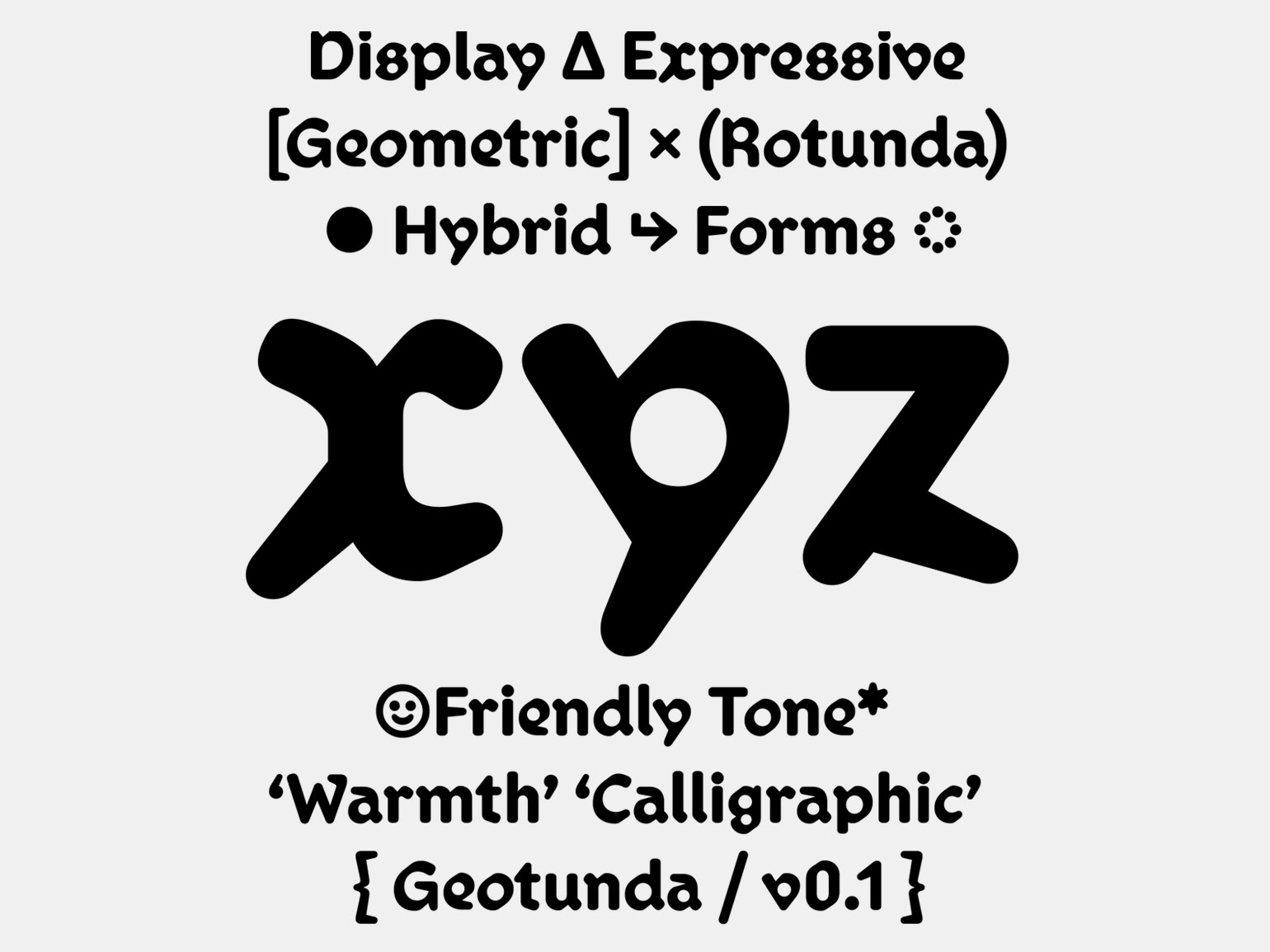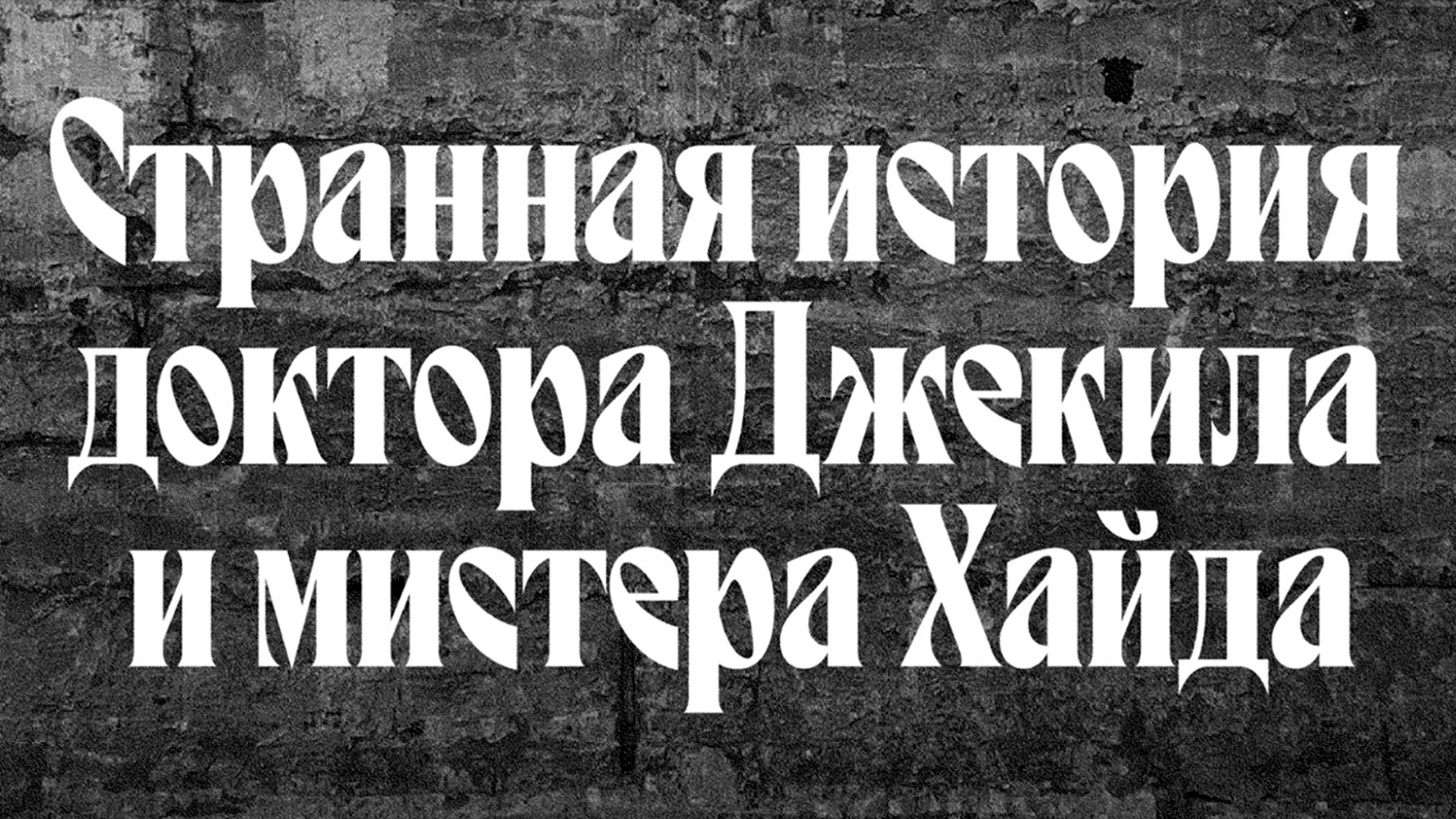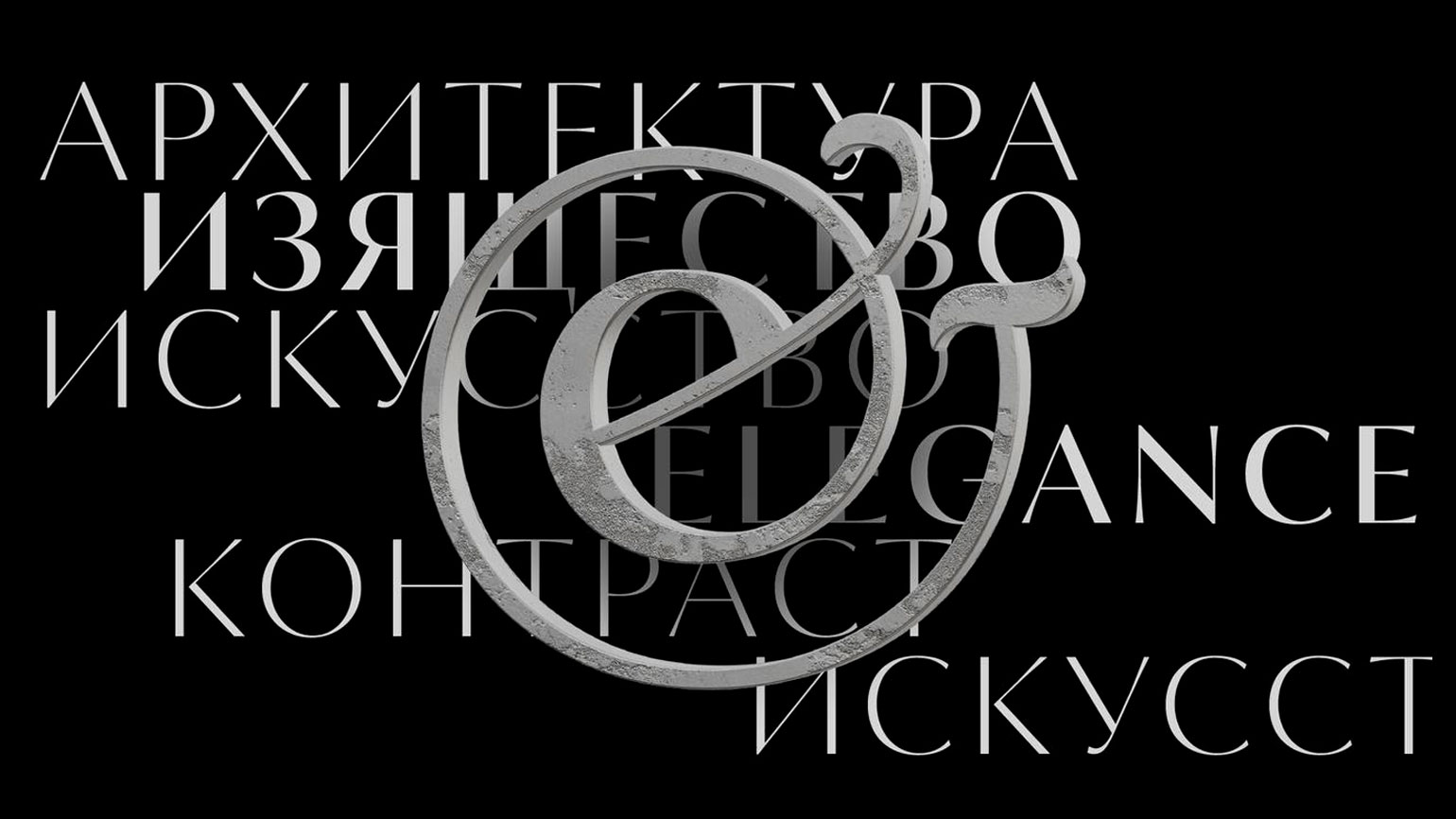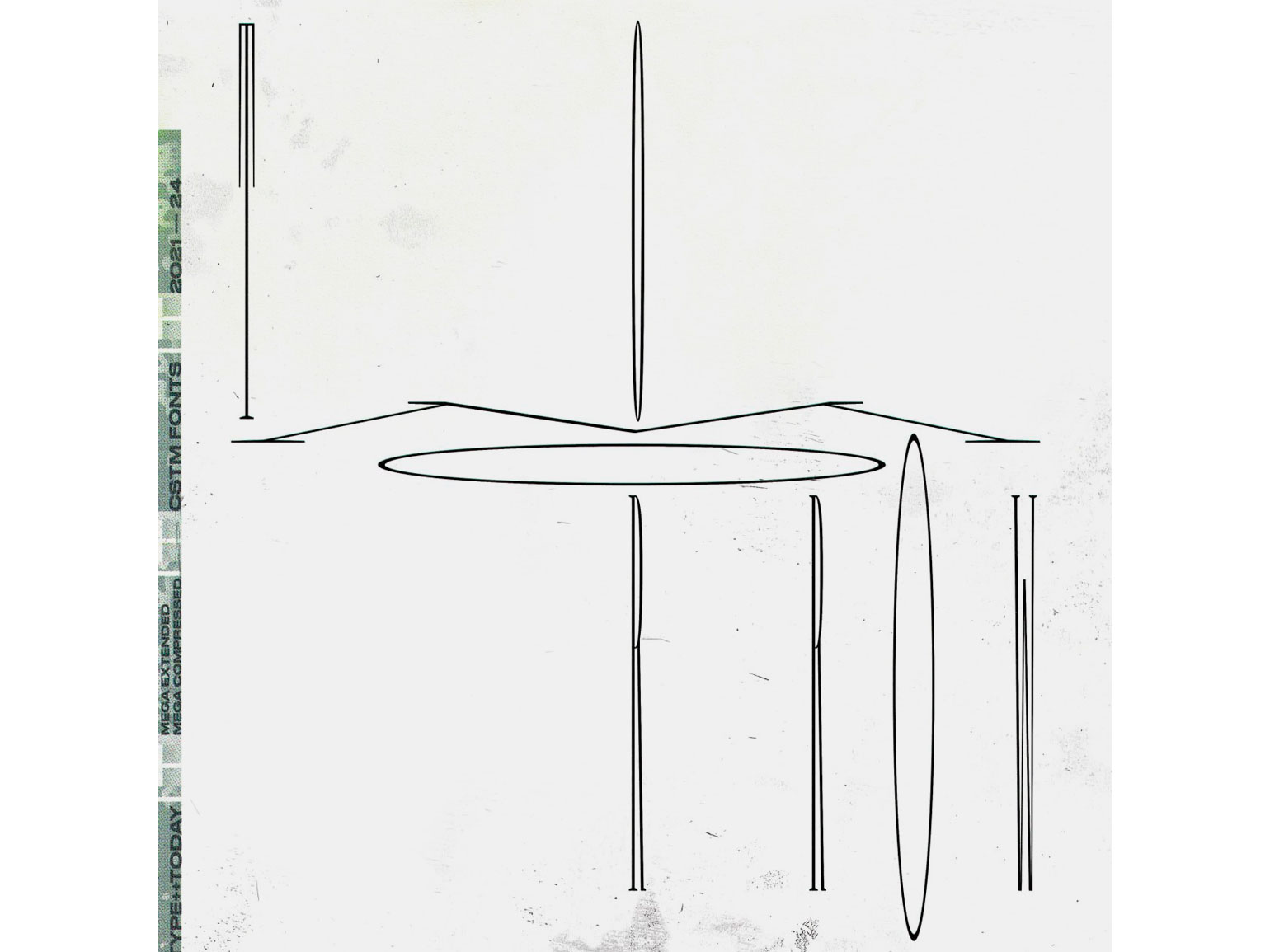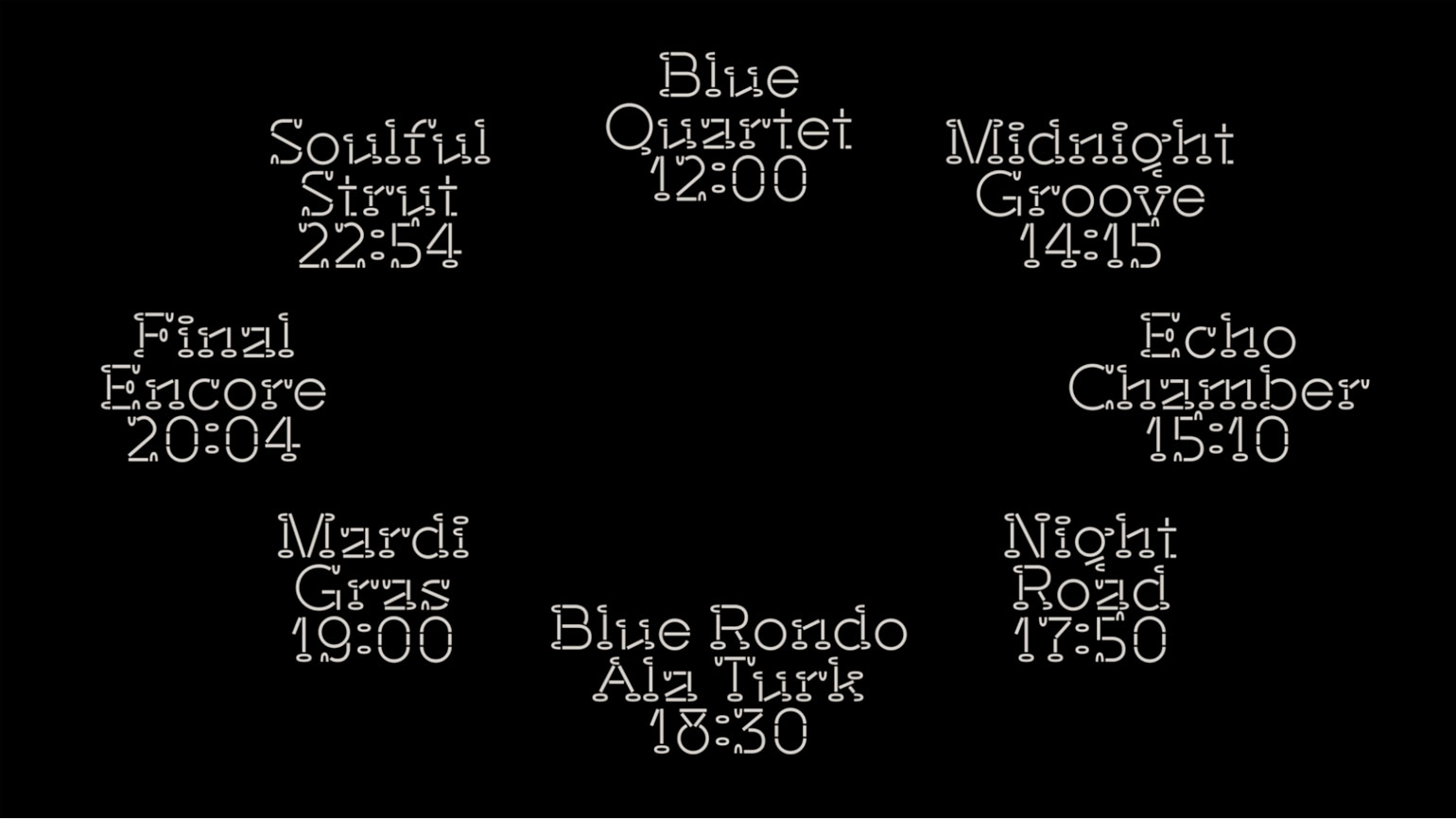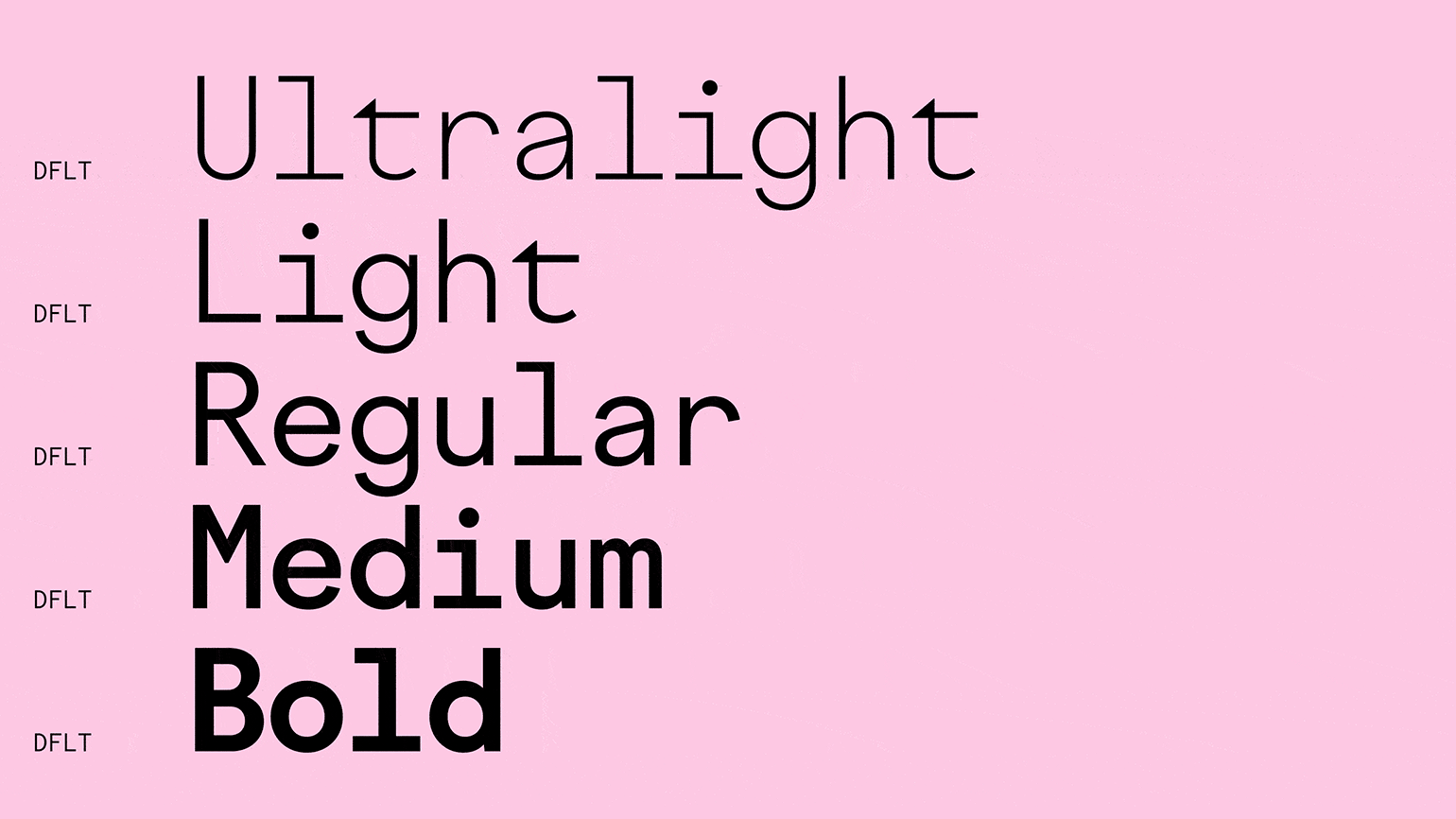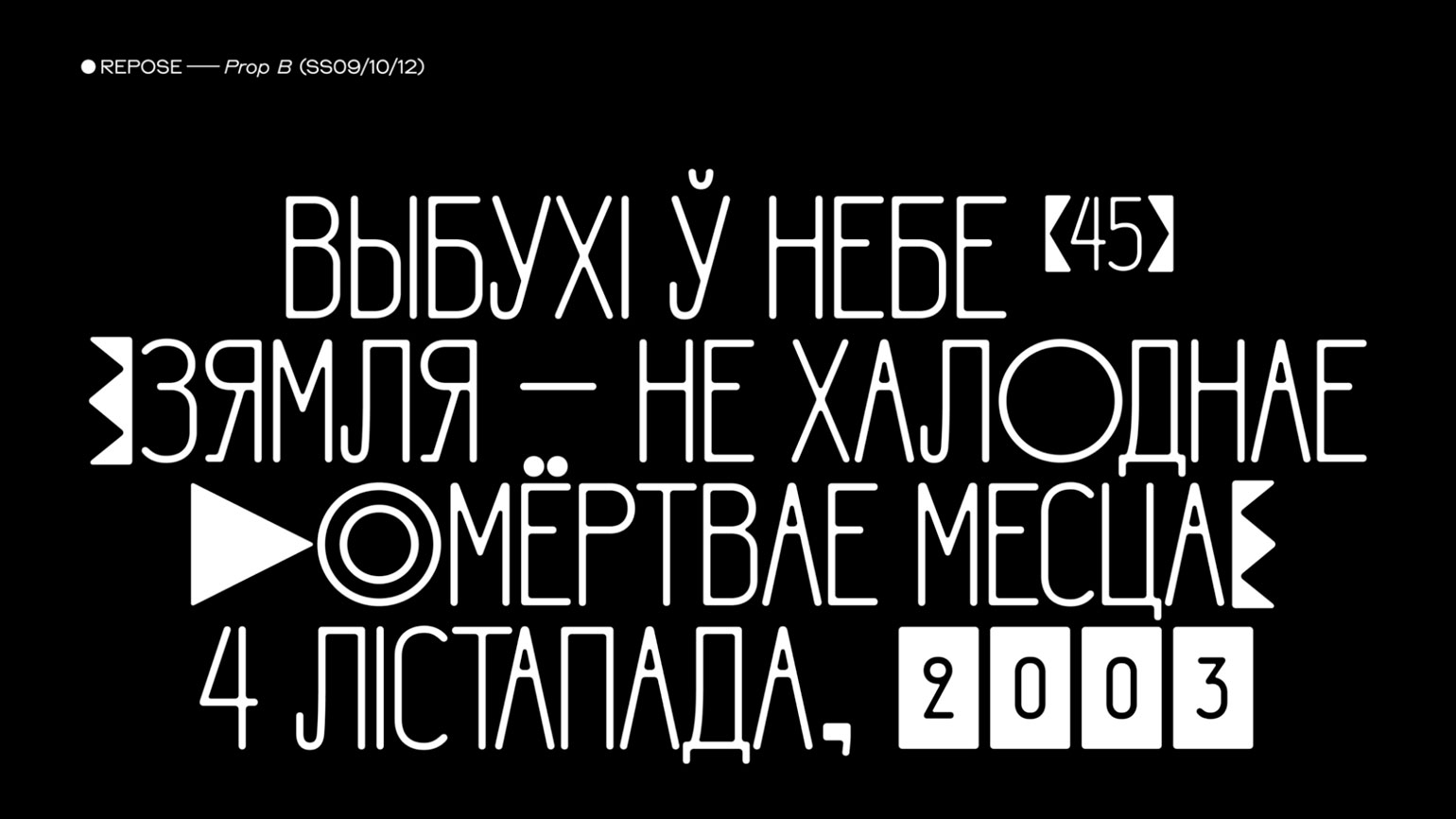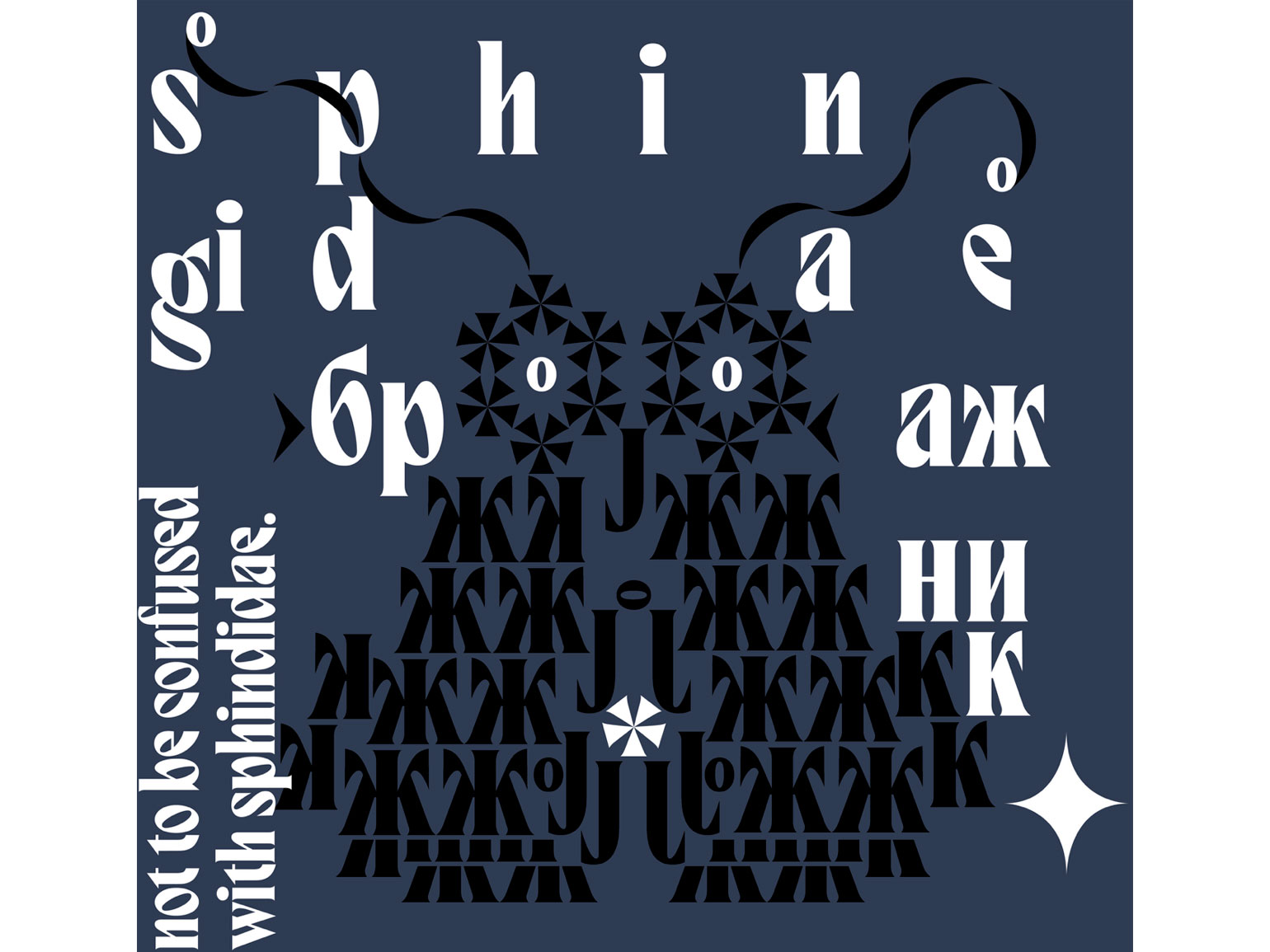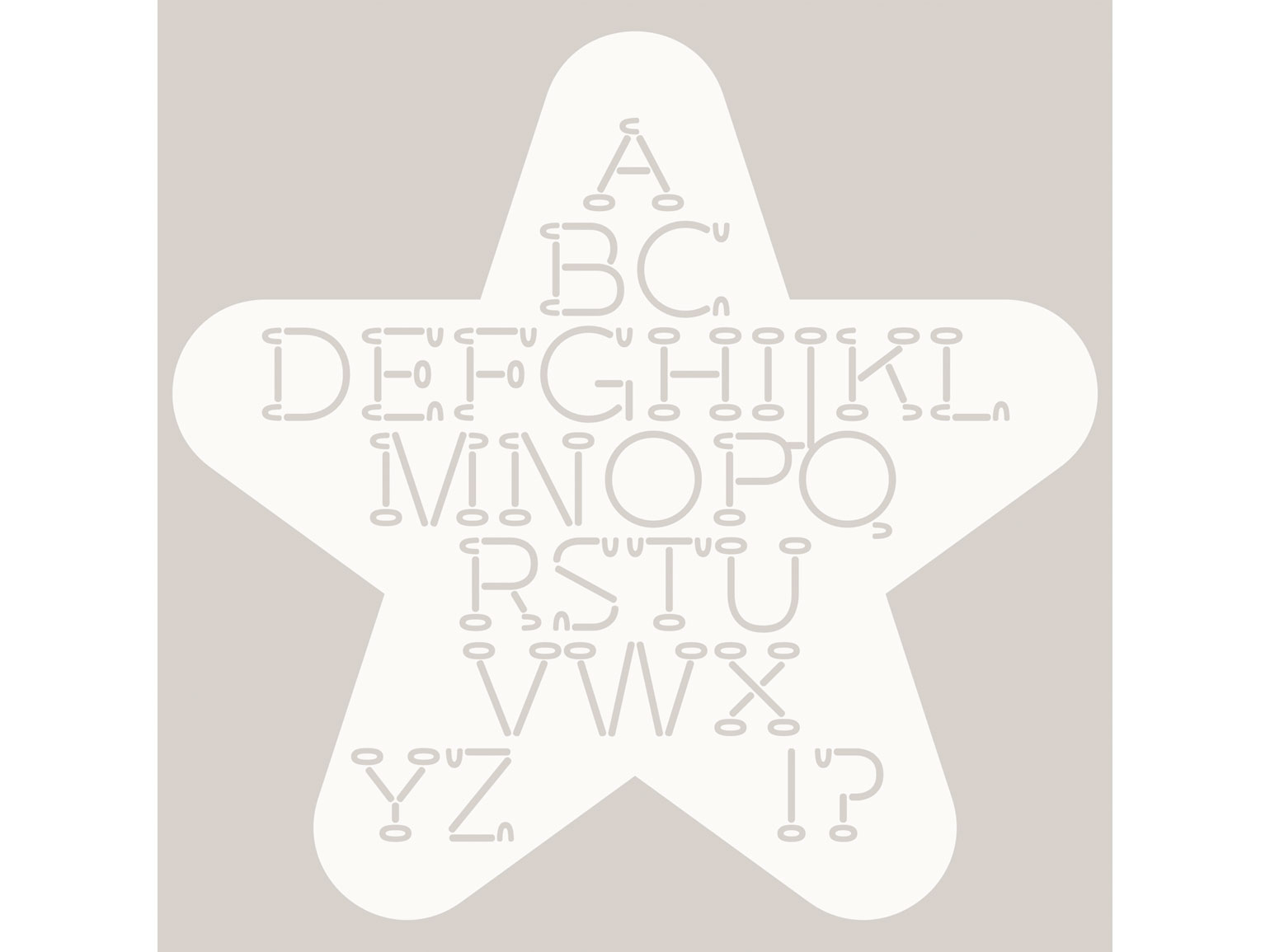
Новые шрифты: элегантная антиква CoFo Raffine, «дружелюбная» Geotunda и перерождение Pragmatica
Эксперты делятся любимыми новинками для экспериментов в дизайн-проектах.
Спросили у шрифтовых дизайнеров и арт-директоров, что сейчас вдохновляет их в типографике: какие новые шрифты заслуживают внимания, где их найти и как использовать для реальных задач.
Repose
Сегодня Филипп Ноймайер — главный человек в кириллице из тех, для кого эта письменность не является родной. Его эксперименты — кладезь интересных и неординарных решений. Я хочу отметить один из таких — свежий релиз Repose. Это тонкий, но от этого не менее брутальный гротеск для ярких и больших надписей. Полностью прописная касса ≠ скучный набор, семейство состоит из двух версий, в которых отличаются графемы, а каждая версия — из трёх вариантов скруглений. Самое время для безумных комбинаций!
Изображение: Филипп Ноймайер / type.today
Guidy
Дипломный проект Матвея Малкина — универсальный открытый геометрический гротеск для навигации. Шрифт уверенно чувствует себя на любой табличке, указателе или схеме. У знаков хорошие просветы и широкие апроши, что делает его прекрасно читаемым с большого расстояния и хорошо различимым в движении.
Guidy поддерживает более ста языков, включая большое количество знаков расширенной кириллицы, а также имеет в комплекте сет иконок с возможностью набора с помощью функций OpenType. А ещё он бесплатный!
Изображение: Матвей Малкин / НИУ ВШЭ
CoFo Raffine
Эта восхитительная, невероятно элегантная антиква авторства Ольги Коваленко — один из самых ярких релизов последних дней. Вдохновлённая титрами из немецкого немого вестерна начала ХХ века, эта гарнитура не оставит равнодушным ни одного любителя букв!
CoFo Raffine разносторонняя, в меру непредсказуемая и небанальная. Из особенностей — утончённый контраст штрихов, разноширинные пропорции, бросающие вызов устоявшимся шрифтовым традициям, а также большое количество лигатур, альтернатив и вариантов с росчерками для яркого, нескучного набора.
Изображение: Ольга Коваленко / Contrast Foundry
Circe Contrast
Хочу рассказать об обновлении шрифта Circe Contrast от студии Paratype. Это грациозный шрифт, без засечек. Он красив, благороден, у него очень широкая линейка начертаний: есть стили для крупных заголовков и текста. Качественный шрифт с кириллицей.
Изображение: Paratype
Pragmatica Next
Расскажу ещё об одном шрифте студии Paratype — о переработке, адаптации по-настоящему культового шрифта Pragmatica. Проект называется Pragmatica Next.
За время своего существования Pragmatica, или, как некоторые ещё её называют, «Русская гельветика», неспроста обрела свой культовый статус. Это нейтральный гротеск с приятными пропорциями букв и качественной кириллицей. А нейтральные гротески, как известно, не теряют своей актуальности и прекрасно вписываются в любую среду. Изначально этот шрифт разрабатывал Владимир Ефимов (1949–2012) — пожалуй, не менее культовая и знаковая в русском шрифтостроении фигура. Pragmatica Next — достойное продолжение его наследия.
Изображение: Paratype
Agse
Шрифт, созданный шрифтовым дизайнером Еленой Новосёловой. Agse — динамичная узкая антиква, подходящая для заголовков. Хорошо работает в паре с более спокойной текстовой антиквой или гротеском.
Изображение: Елена Новосёлова / type.today
Изображение: Елена Новосёлова / @masha_bazil / type.today
Изображение: Елена Новосёлова / @mishatitovaprint / type.today
Lufta
Шрифт дизайнера Арины Шокаревой. Дружелюбная антиква, которая будет хорошо работать на светоотражающих патчах для одежды и в айдентике DeepTechech-стартапа.
Изображение: Арина Шокарева
Владимир Аносов
Шрифтовой дизайнер, каллиграф, преподаватель Школы дизайна НИУ ВШЭ СПб, преподаватель онлайн-курса в «Щёлочи», основатель сообщества Typofriends
Aspid Stencil
Наглая «хрустящая» антиква с ярким характером, вроде и дружелюбная, но коварная. Будто твой лечащий врач, который знает о тебе всё, но которому можно доверять. Легко может стать мощнейшим элементом любого дизайна, особенно в умелых руках.
Изображение: Дмитрий Голуб / Роман Саломатин / студия Bolditalic
Geotunda
Один из самых ярких шрифтов, которые видел в последнее время. Отличный синтез исторических почерков и современного шрифтового дизайна. Довольно дружелюбный, немного весёлый, кажется, может работать в разных размерах. В шрифте нет кириллицы, к сожалению или к счастью.